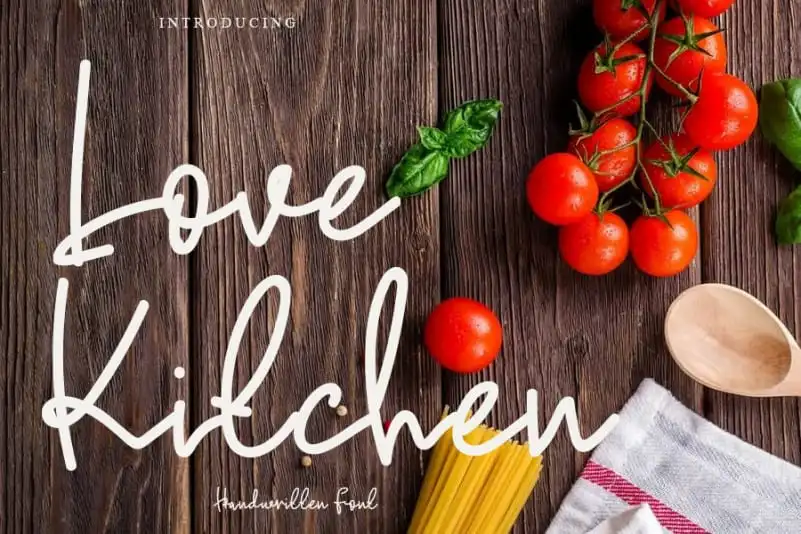
Love Kitchen Handwritten Font – Download Grátis
A fonte Love Kitchen Handwritten Font é uma mão-dura escrita com cara de amor que irradia carinho e alegria. Ideal para quem busca uma fonte que traga um toque divertido e pessoal aos seus projetos digitais, seja em design gráfico, editoração ou até mesmo em criação de conteúdo online. Suas linhas leves e curvas suaves criam um toque familiar e acolhedor, dando às suas publicações uma cara autêntica e única. Ela é perfeita para aqueles que querem trazer um pouco mais de personalidade aos seus materiais digitais, sem sair do estilo elegante da escrita à mão. A levincreative criou essa fonte para aqueles que apreciam detalhes delicados em suas criações. Com um toque cítrico e uma pitada de irreverência, a Love Kitchen Handwritten Font é perfeita para adicionar um toque encantador a qualquer projeto digital. Não importa o tamanho do seu projeto ou qual seja sua finalidade, essa fonte será uma escolha inteligente. Você vai amar a diferença que ela faz em suas criações.